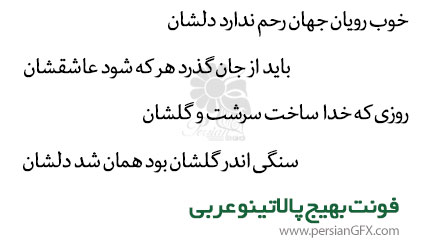
فونت بهیج پالاتینو عربی از سری فونتهای تصحیح شده ایست که توسط یک آکادمی مجازی توسعه یافته است. این فونتها تصحیح شده ی فونتهای رایج فارسی، عربی نظیر Nazanin ،Nassim و… می باشد. خوبی این فونتها نسبت به سایر سری ها اینست که ویرایشهایی نیز برای حروف لاتین، اعراب و علایم صورت گرفته و کاراکترهایی گنجانده شده است که باعث کاملتر شدن این فونتها نسبت به سایر نموده است مثلا در برخی از فونتهای های رایج حروف لاتین پشتیبانی نمی شود و هنگام نمایش برای حروف لاتین از فونتهای دیگر نظیر Tahoma و یا Arial فراخوانی می شود و به همین دلیل است که هنگام تخصیص آنها در وب از چندین فونت پشت سر هم استفاده می شود.